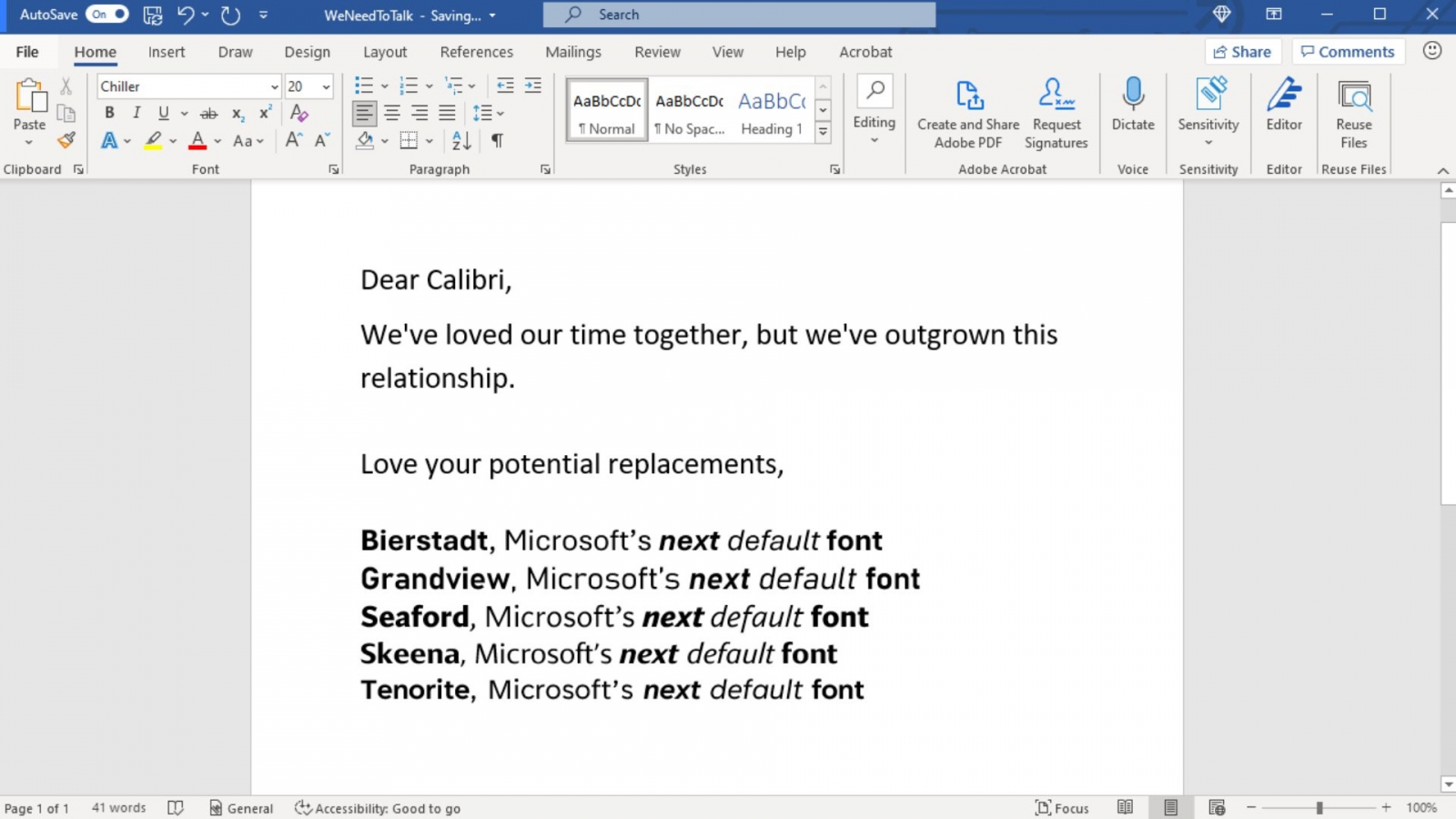
Microsoft заказала у дизайнеров разработку пяти оригинальных пользовательских шрифтов, которые в итоге заменят Calibri в 2022 году. «Calibri был шрифтом по умолчанию для продуктов Microsoft с 2007 года, и сейчас пришло время двигаться дальше», — рассказала Sostav пресс-служба компании.
Новым базовым шрифтом станет тот, который пользователи выберут из предложенных: Bierstadt, Grandview, Seaford, Skeena или Tenorite. Дизайнеры Microsoft старались разработать удобные для чтения шрифты, которые приятны глазу и не имеют засечек и штрихов. Также разработчики учитывали, как пользователи будут использовать шрифты для своих документов.
Например, узкое расположение символов Tenorite позволяет разместить больше слов в строке, что может быть полезно в презентациях PowerPoint и в электронных таблицах Excel. Знаки препинания дизайнеры также сделали яркими и крупными, чтобы читатель обращал на них внимание.
Некоторые шрифты вдохновлены европейскими стилями печати. Так, Grandview стремится к стилю немецких дорожных знаков, а шрифт Bierstadt вдохновлен швейцарской типографикой середины прошлого века. Вариант Skeena повторяет стиль популярных в 20 веке шрифтов с засечками, однако за счет их отсутствия читается легче.
Microsoft предложила всем желающим поделиться в соцсетях своим фаворитом. Несмотря на итоговый выбор, все из указанных вариантов будут доступны пользователям в приложениях Office.